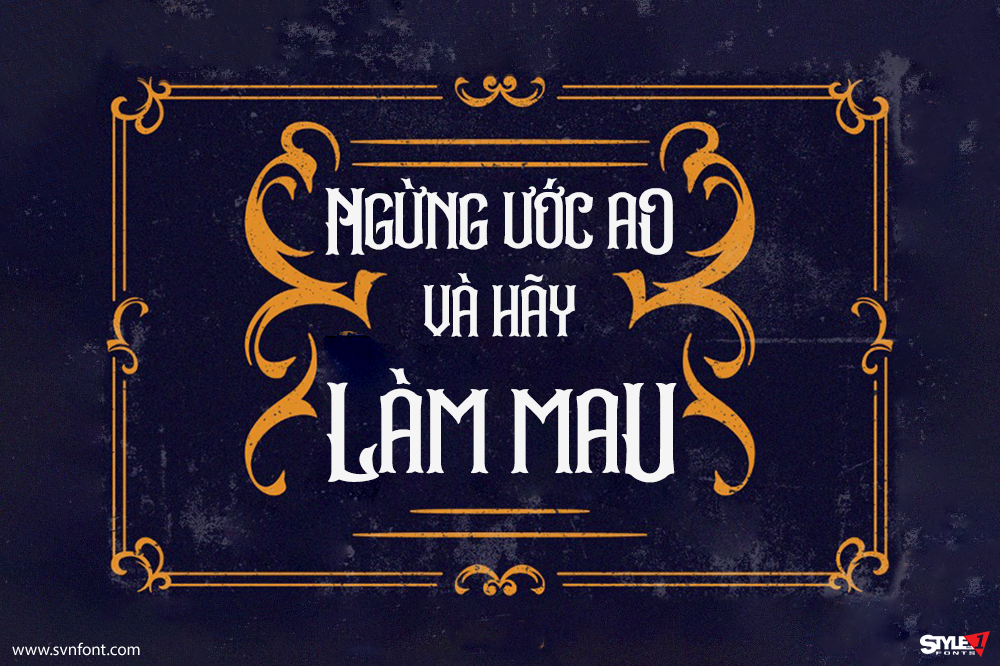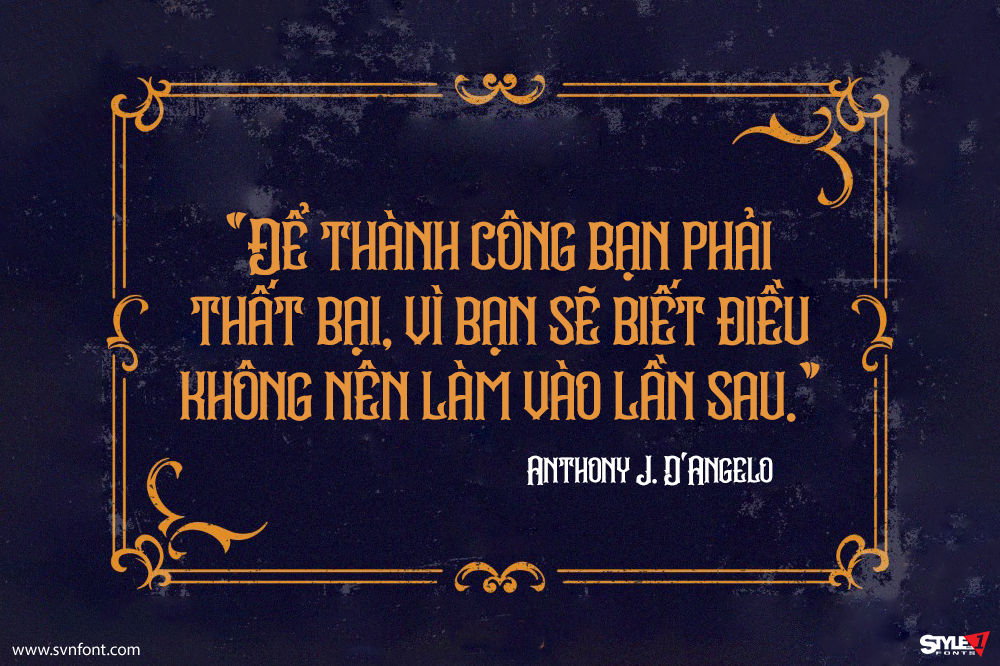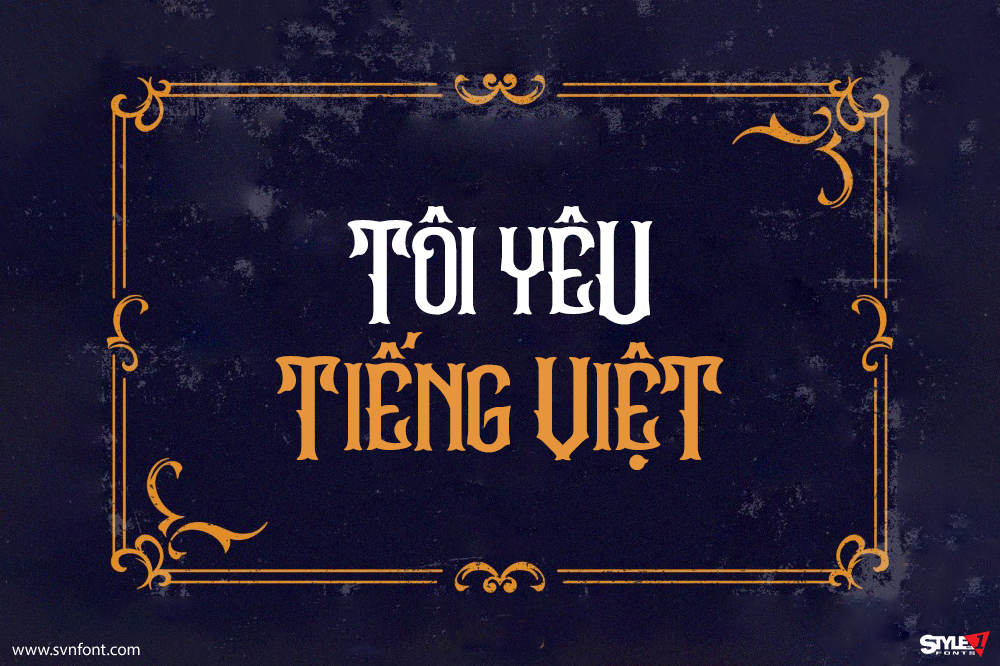
Stradas là một display font ấn tượng, phù hợp cho nhiều loại dự án như branding, lettering, in áo thun và nhiều ứng dụng sáng tạo khác. Font mang phong cách mạnh mẽ, dễ thu hút ánh nhìn và giúp thiết kế của bạn trở nên nổi bật hơn.
Nhà thiết kế: Donis Miftahudin
Nhà phát hành: Din Studio